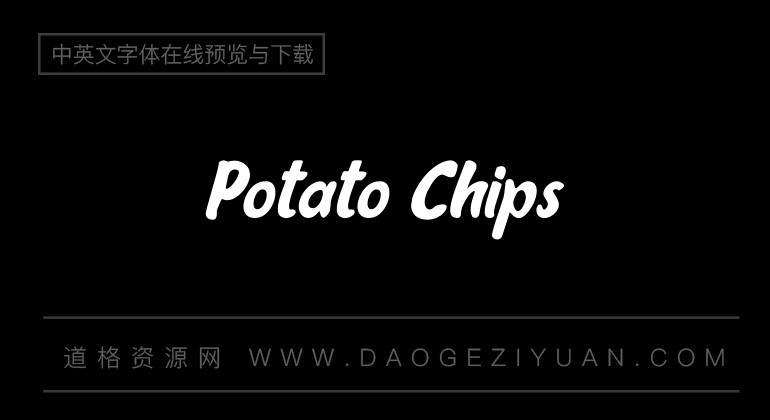
Potato Chips
Potato Chips 字体是一款粗体字体,它的特点是拥有清晰的曲线,细节处理精致,可以更好的表达文字的意思。它的字母形状大多为圆形,比较圆润,显得更加柔和,更容易被人接受。此外,它还具有较高的可读性,在距离较远时也能保持清晰的文字。
Potato Chips是一款非常不错的手写艺术字体,具有很好的视觉感,适合于文化类的宣传设计、商业类品牌的广告和产品包装设计以及个性化文字排版等较多场景。